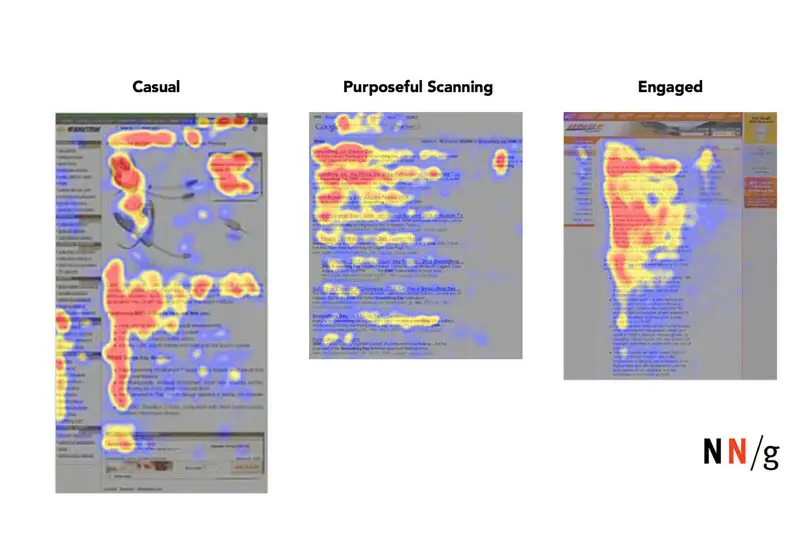
如果品牌正在考虑使用字体解决方案,可以有如下三种不同的选择:
- 委托定制字体
- 在现有字体基础上,根据品牌宗旨及形象进行修改
- 从现有字体库中选择字体
那么,哪种方法是正确的呢? 是的,正如您想的那样,答案是:视情况而定。毕竟,字体是品牌标识的重要组成部分,它可以传达品牌的基调、信息和个性。在一个由 Monotype 公司字体设计总监 Charles Nix 主持的题目为“字体排印困境:定制、修改还是从字体库选择”的会议上,一个优秀的创意小组讨论了各种字体的好处及需要考虑的问题。
定制字体
首先,专题小组着重说明了定制字体。定制字体的最大的好处是拥有字体的所有权。拥有知识产权,即在未经允许的情况下任何人不得使用,因此该设计就成了您品牌所独有的。设计上无需妥协,而且还可以构建能同时满足当前及未来技术需求的设计。定制字体对于正着手重塑品牌的公司来说是有意义的,因为它们可以帮助公司定义和激活新的视觉识别。
丰田就是这种情况,该公司与 Monotype 及盛世长城(Saatchi&Saatchi)合作开发了一款新的定制字体。在会议上,Monotype 字体创意总监 Steve Matteson 和盛世长城的首席创意官 Jason Schragger 分享了他们共同开发这款字体的过程。Schragger 负责监管丰田 2018 年全球奥运会和残奥会的创意活动,包括最近推出的“全民移动”(Mobility for All)活动,他指出了在开始定制字体项目时,有创造性地尝试非常重要。丰田公司对这种做法表示赞同,他们认为这是构建一款最终满足其需求的字体的重要环节。
Steve Matteson 是 Open Sans 字体的设计师,这款字体在超过 1700 万个网站上使用,他讨论了设计汽车和设计字体之间的相似之处,即在两种情况下,设计师开始都是使用静态产品,然后改变比例来确定最终的风格和个性。当然,字体的静态特性使它很难传达动感的效果,但对于丰田来说,作为一家被驾乘者所信赖的企业,重要的是字体必须符合公司的品牌使命。因此,团队通过使字符互相引导而实现设计,就像画笔笔触一样,给人一种“动感”的感觉。
修改字体
接下来,专题小组讨论了为了满足特定需求或者美学标准而选择修改字体的好处。当然,设计可以改变的程度是有限制的,但像 Monotype Studio 的字体专家就可以清楚地说明这些限制,然后与您一起选择适合的初始字体并根据您的喜好进行修改。修改后的字体非常适合那些想要独一无二的字体、但又由于产品发布等原因没有时间定制的品牌。
Thumbtack 公司的设计经理 Andrew Johnson 分享了他们是如何决定在 FF Mark 字体的基础上修改其品牌 logo 中的八个字符来重塑品牌的。Johnson 是 Thumbtack 公司的品牌设计团队的领导者,该公司能让数百万客户在全国范围内找到和雇佣他们需要的服务者。在过去的一年里,他的团队已经对品牌战略、视觉识别以及品牌活动进行了全面的反思,以应对日益激烈的竞争和不断变化的客户需求。正如他所说,“我们想改变一切,除了公司名字。”
Johnson 和他的团队喜欢采用混合的方式修改字体。“我们可以基于字体设计师的才华,和他们一起设计出属于我们自己的东西。”FF Mark 的那点怪异特征刚好适合该品牌,而且它还提供了较大的字符集。有趣的是,字体修改之后,字体文件的大小还减少了 40%,这使得网站以及品牌 app 的加载速度更快了,从而转化为实实在在的商业价值。
字体库中的字体
最后,专题小组探讨了使用字体库里的字体需要注意的事情。正如 Charles 所说的那样,“世界上有成千上万种永恒的、独特的字体,它们都已经准备就绪,等待被授权并投入到您的创作中去。”从字体库中选择字体是一种简单快捷的解决方案。这里有大量的设计可供选择,而且字体工作室可以帮助您找到与您的视觉形象及品牌价值相一致的字体。
Hearst 杂志的数字媒体用户体验和产品设计创意总监 Theresa Mershon 解释了她的团队是如何使用 Monotype 字体库中的一系列字体来实现创作自由以及数字化灵活性的。Mershon 为出版商设计数字化体验已经超过15年了,现在负责监管一个国际化平台的全球的设计及用户体验,这个平台为几十种最知名的出版物提供支持,包括 Cosmopolitan,ELLE 和 Esquire。
由于有这么多不同的网点和渠道,保持品牌标识的一致性非常重要,也具有极大的挑战性。例如,对于 Cosmopolitan 来说,仅在 Snapchat 上就有 190 万女性消费其内容,而不是登陆他们的网站,因此 Cosmopolitan 所使用的字体就成了保持品牌一致性的工具。正如 Mershon 所指出的,“我们让排印驱动品牌化”
Mershon 还分享了一个有趣的热力图,它展示了不同的内容消费者浏览网站的方式,这是基于用户随意浏览和有针对性的阅读而做出的分析。
她说:“当我和编辑一起工作时,我告诉他们要把注意力放在第一句话上,因为这是唯一能让人们 100% 阅读的部分。”